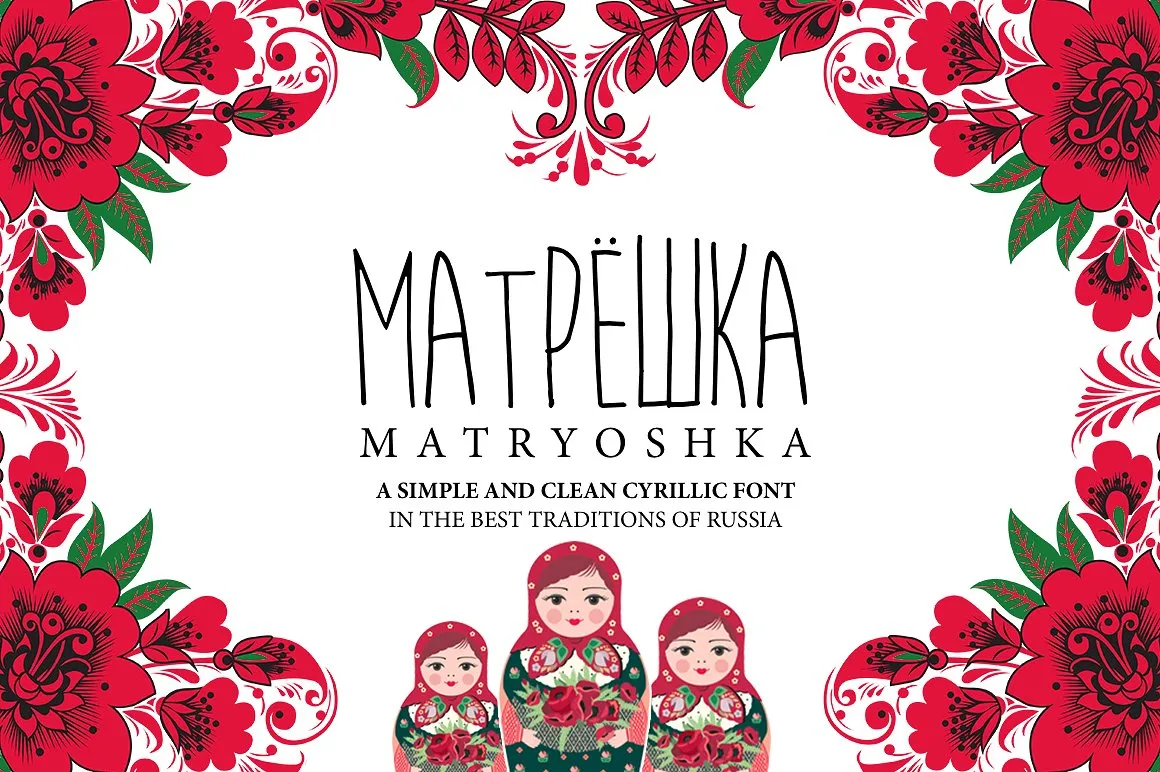
Кириллический шрифт
Создание аутентичной типографики, вдохновленной традиционными элементами, для использования в современных дизайн-проектах. В материалах представлена проработка символов кириллического алфавита с сохранением стилистической целостности и корректной геометрии знаков. Инструментарий позволяет внедрять готовые начертания в айдентику, полиграфию или веб-интерфейсы, требующие нестандартной шрифтовой подачи.